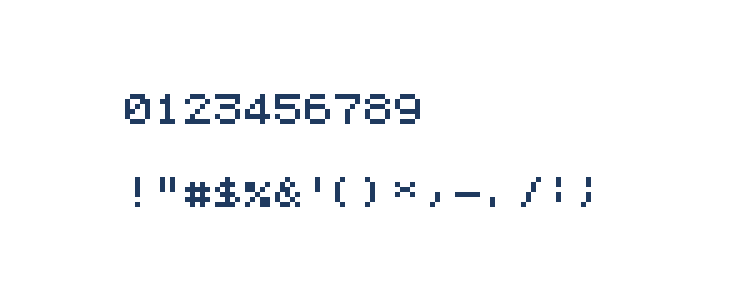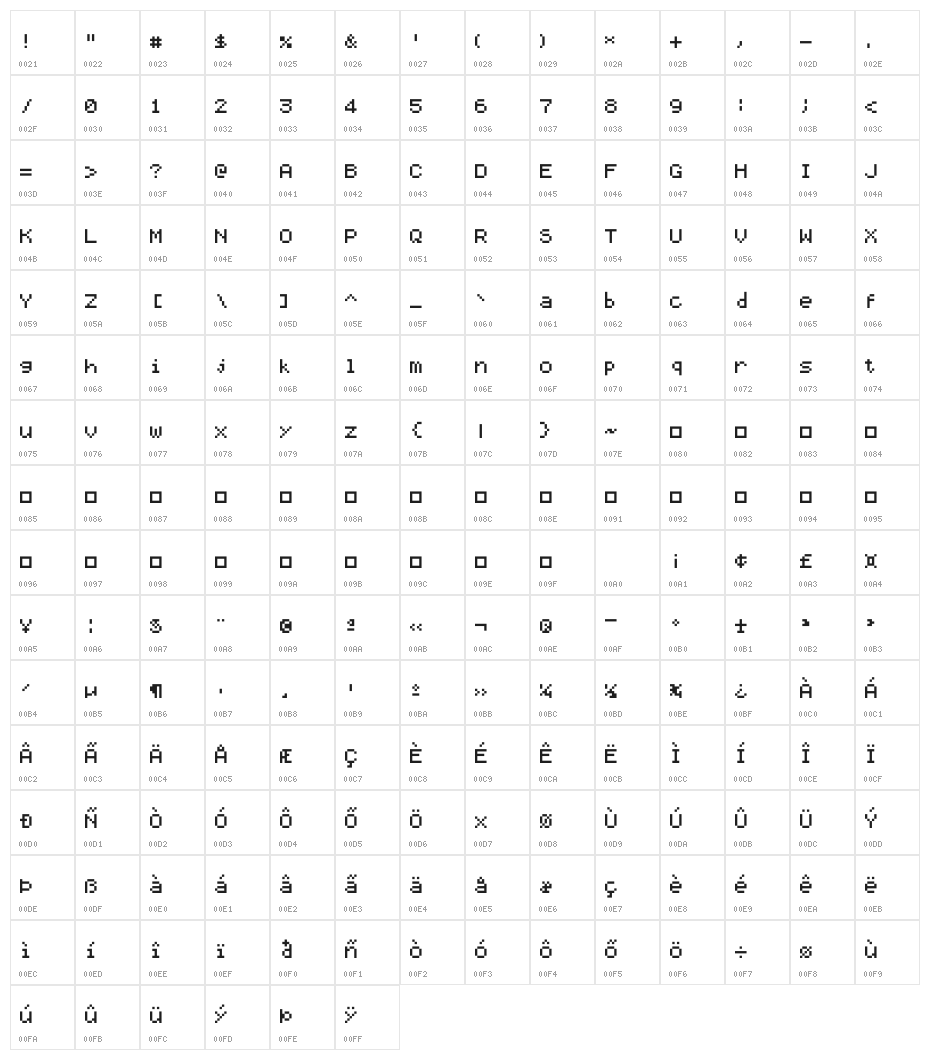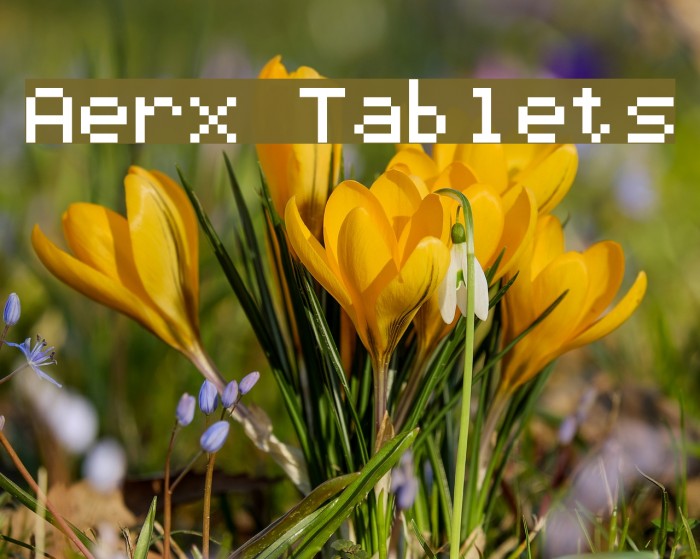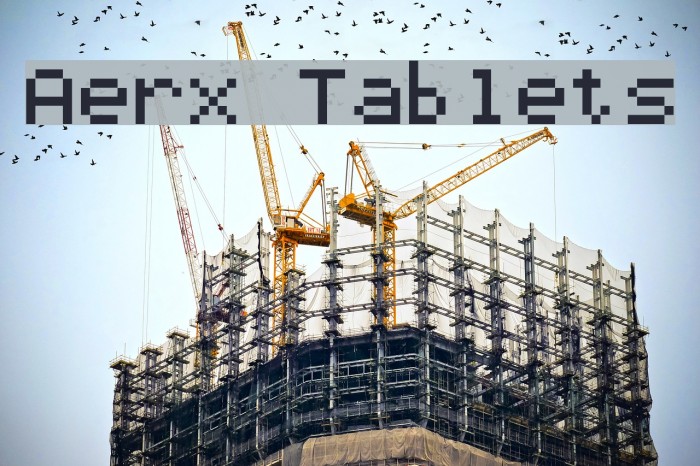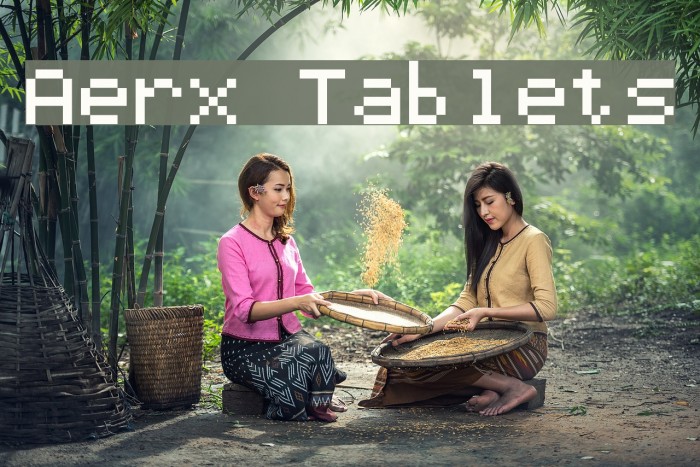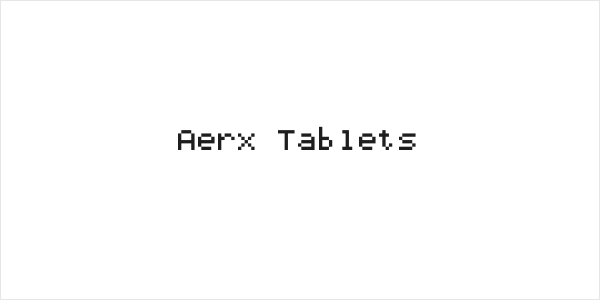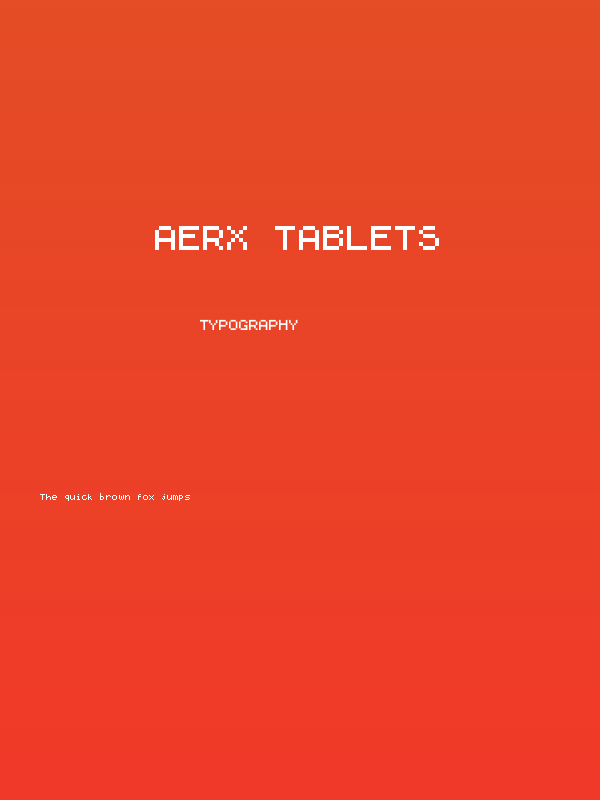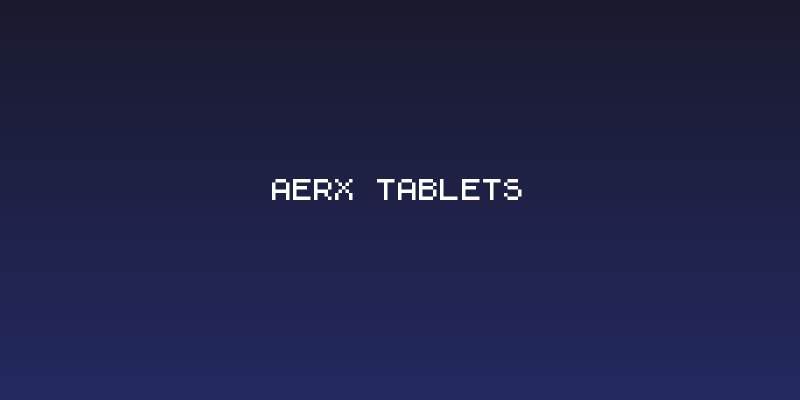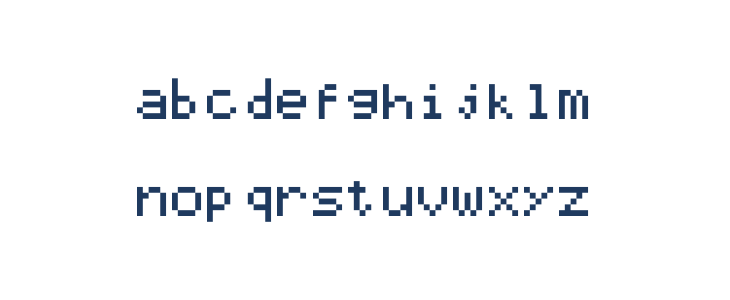
Aerx Tablets Font
✎ Pixel
| Categorie | Pixel |
| Caso d'uso | Logos, Headlines, Digital Art |
| Progetti proposti | Ideal for retro video game designs, digital art projects, tech-themed posters, and any creative work that seeks to evoke a sense of nostalgia for early computing. |